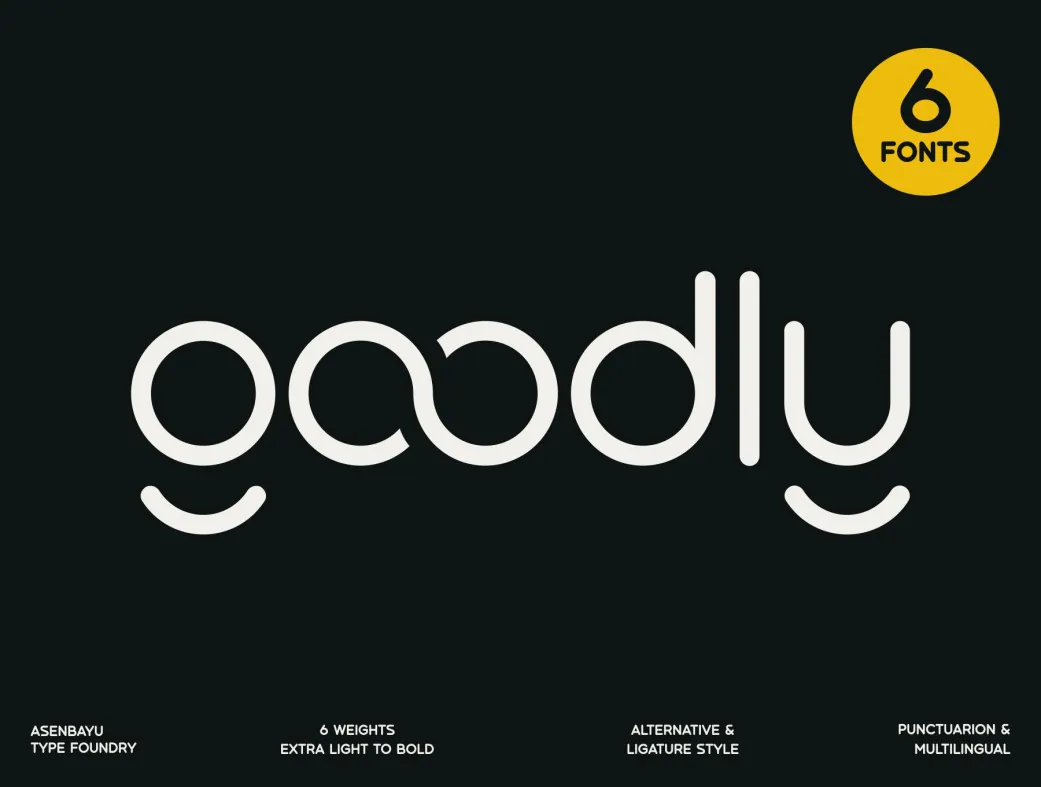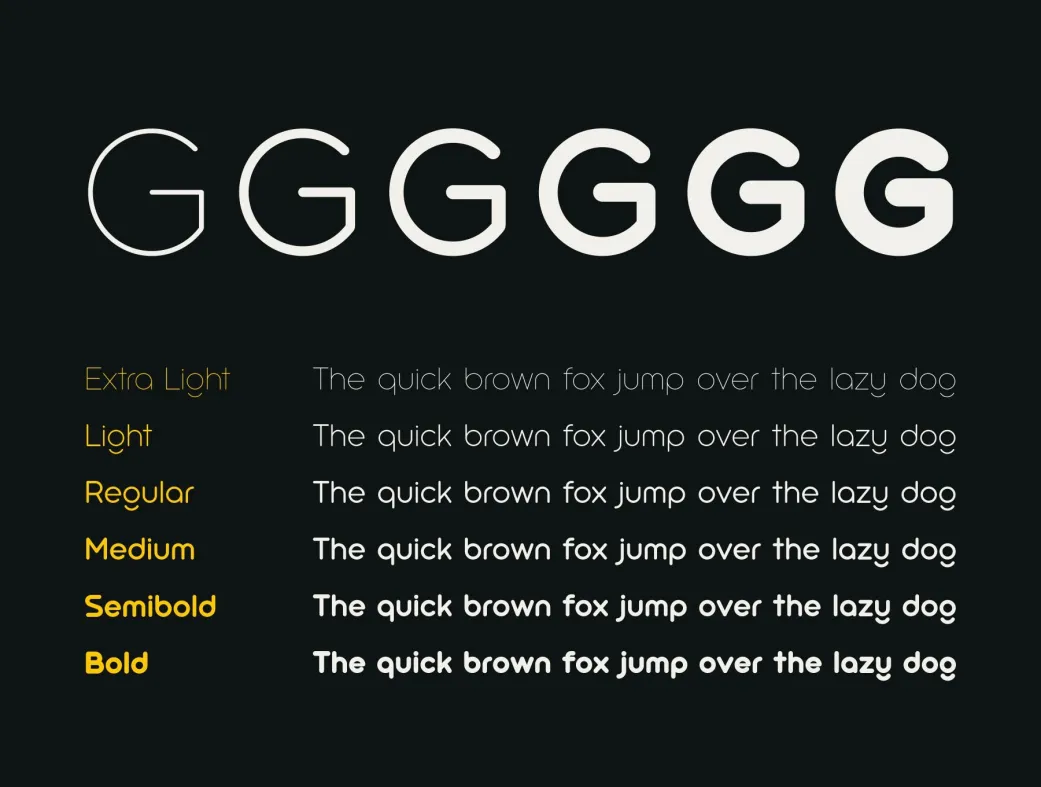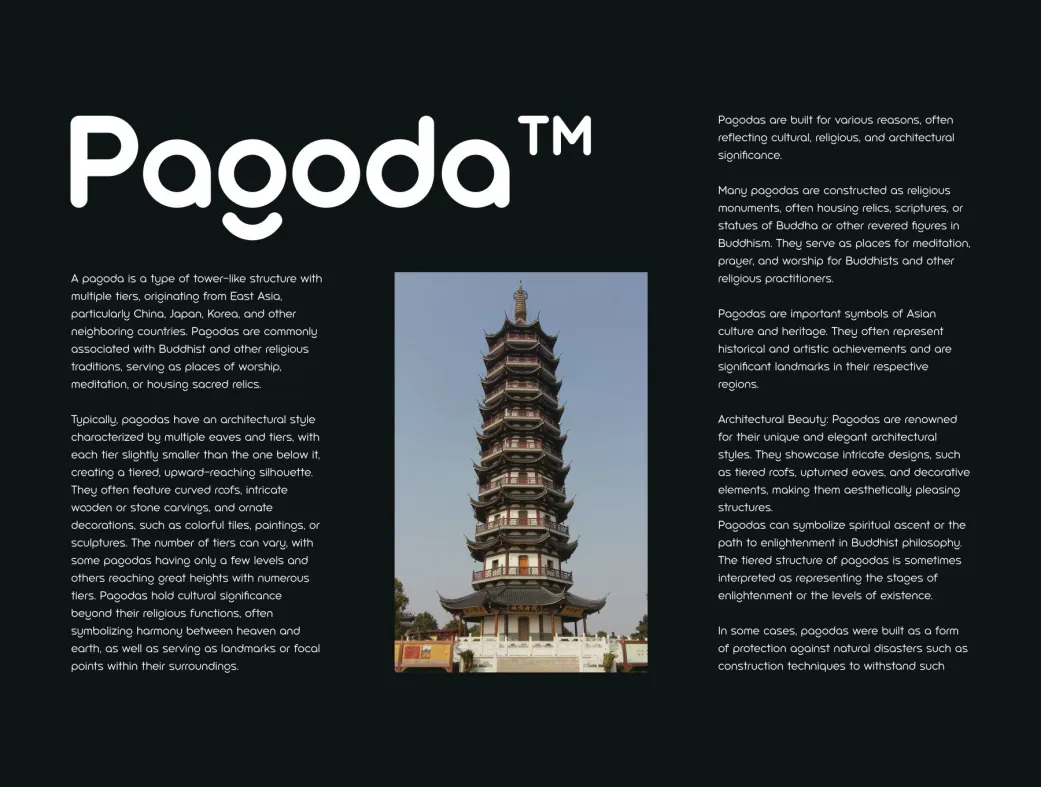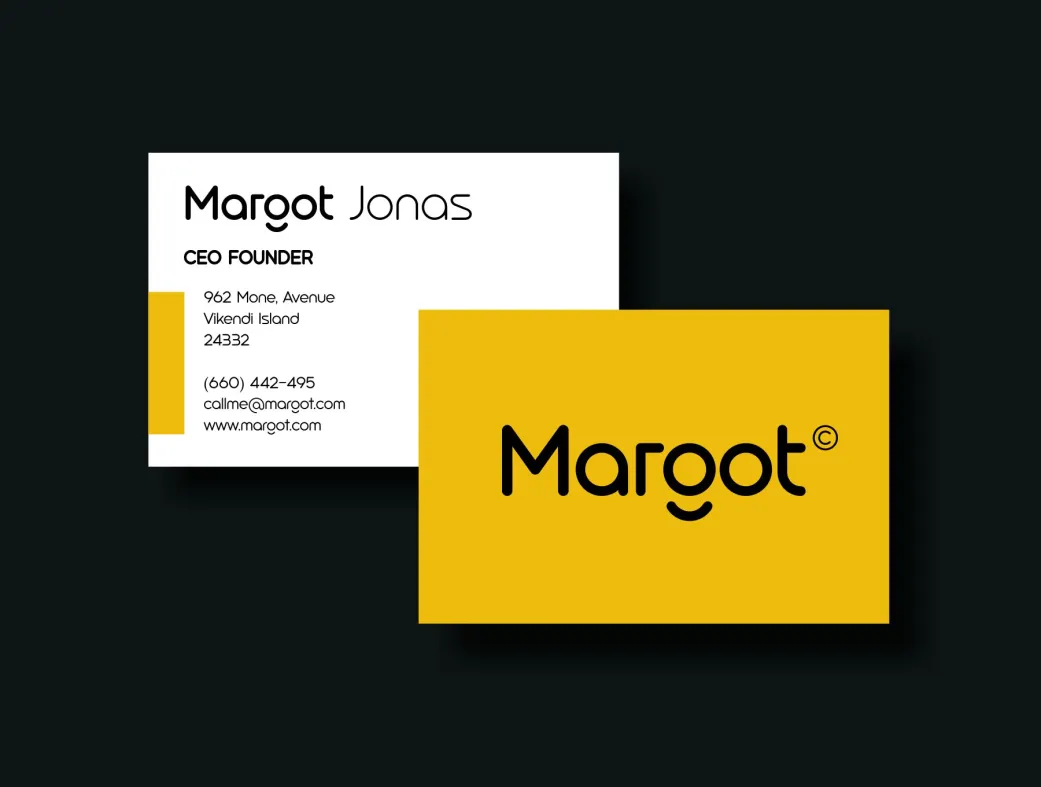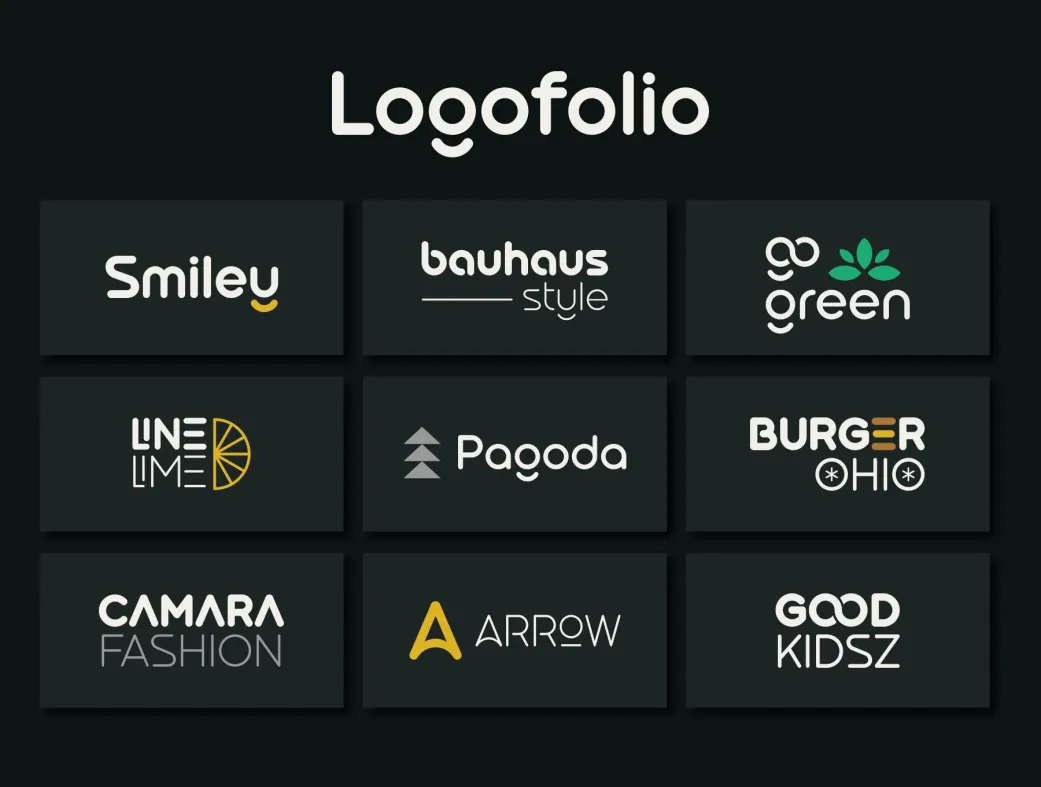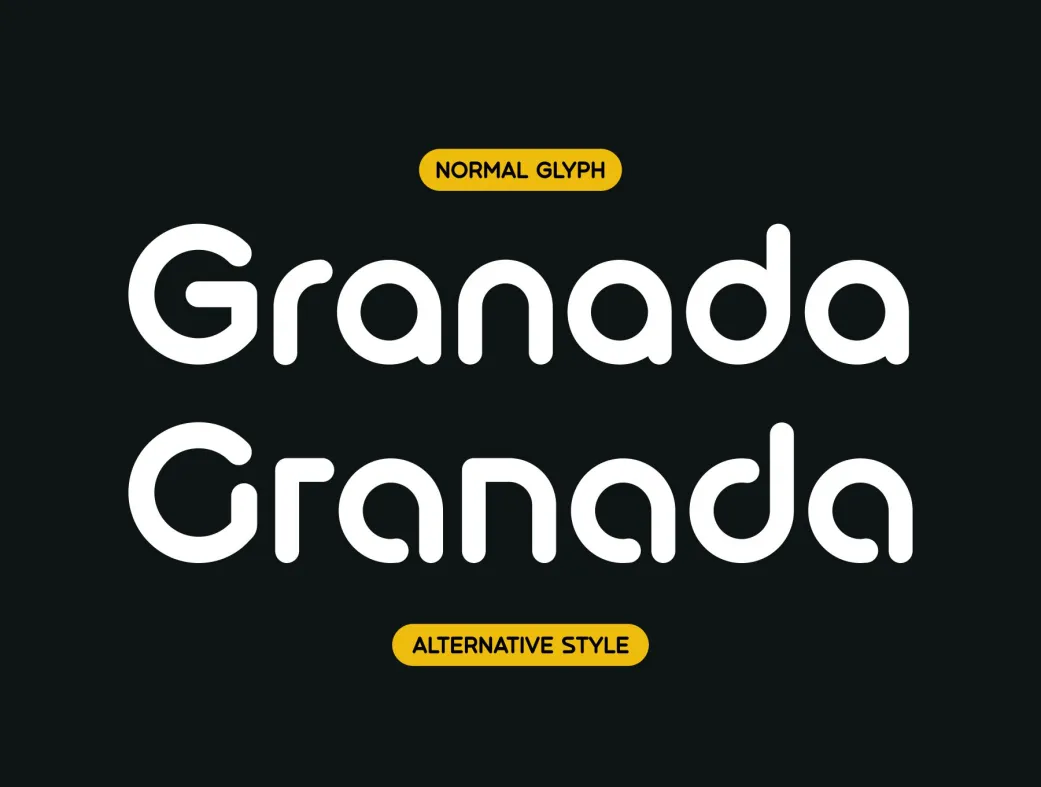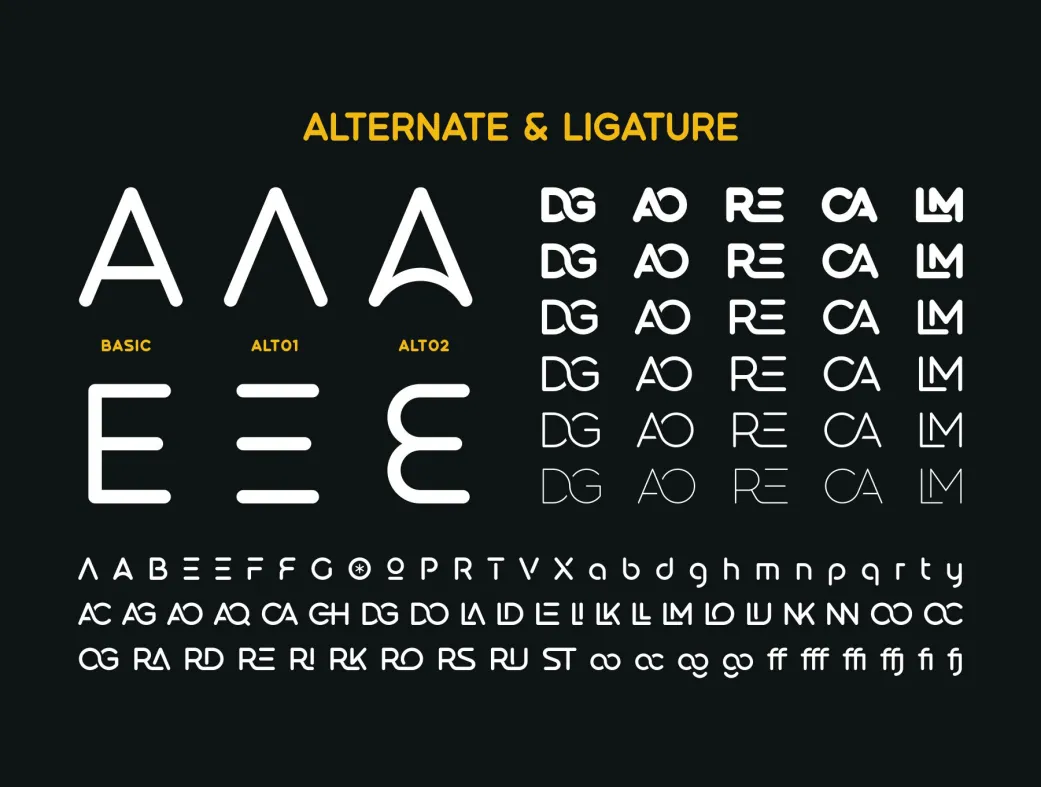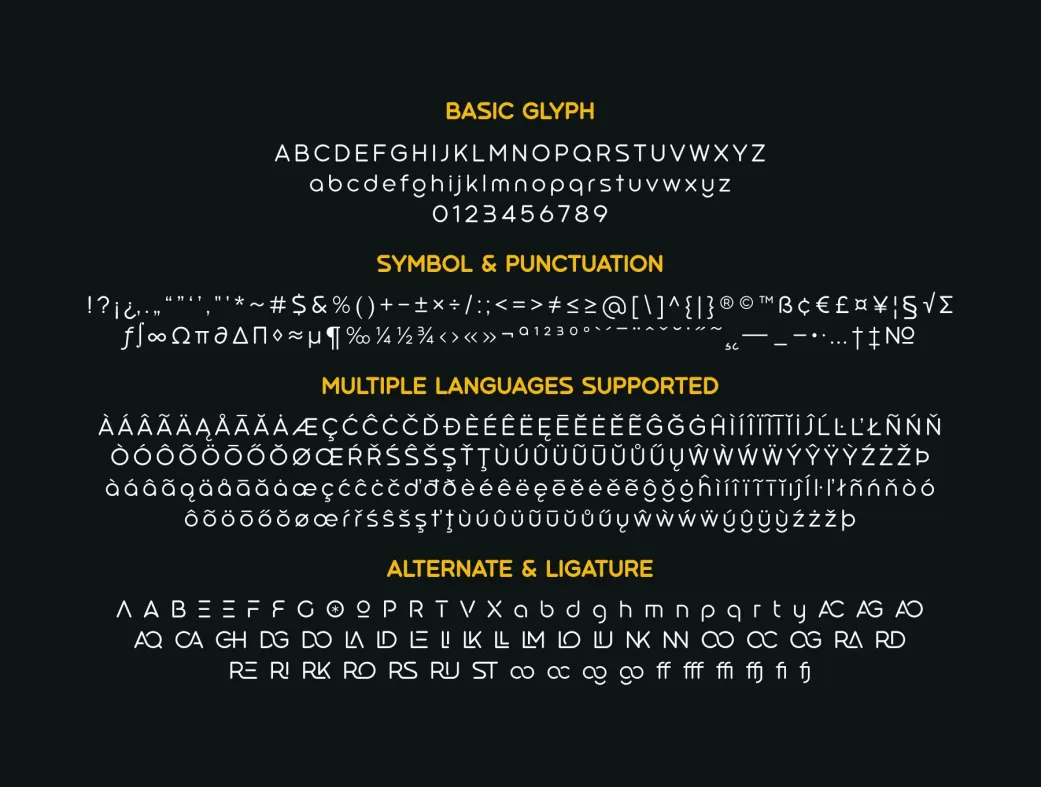
خانواده فونت‌ گودلی | Goodly
خانواده فونت Goodly با ۶ وزن مختلف، طراحی‌های شما را به زیبایی متمایز می‌کند!
Goodly Fonts Family
خانواده فونت‌ گودلی | Goodly Font Family
خانواده فونت‌ Goodly یک مجموعه فونت مدرن و گرد با طراحی سنس سریف است که شامل ۶ وزن مختلف می‌باشد. این فونت به شما کمک می‌کند تا تعادل ایده‌آل طراحی را بین مدرنیته و سادگی برقرار کنید. شکل گرد این فونت‌ها می‌تواند احساس دوستی را ایجاد کند، در حالی که همزمان ظاهری حرفه‌ای نیز دارند.
خانواده فونت Goodly با ۶ وزن مختلف، قابلیت‌های متنوعی را برای طراحان فراهم می‌آورد. این فونت‌ها از فرمت‌های OTF، TTF و WOFF پشتیبانی می‌کنند و دارای گلیف‌های استاندارد هستند. همچنین، Goodly شامل جایگزین‌های استایلی و لیگاتورهای جذابی است که به شما امکان می‌دهد طراحی‌هایی منحصر به فرد و زیبا ایجاد کنید. با وجود پشتیبانی از چندین زبان، این فونت برای پروژه‌های بین‌المللی نیز مناسب است و می‌تواند در طراحی برچسب‌های مد روز، لوگوهای خاص و برندینگ، طراحی پوسترها، مد و بسیاری دیگر مورد استفاده قرار گیرد.
این فونت برای طراحان حرفه‌ای و مبتدی مناسب است. طراحان حرفه‌ای می‌توانند از تنوع وزن‌ها و جایگزین‌های استایلی برای ایجاد پروژه‌های خاص استفاده کنند. در عین حال، مبتدیان نیز می‌توانند به سادگی از این فونت در طراحی‌های خود بهره‌برداری کنند و به راحتی با آن آشنا شوند. توصیه می‌شود که در طراحی‌های برندینگ و تبلیغات، از این فونت برای جذب مخاطب و ایجاد احساس مثبت استفاده شود.
1. آیا فونت Goodly شامل وزن‌های مختلف است؟
بله، خانواده فونت Goodly شامل ۶ وزن مختلف است که به شما امکان می‌دهد تا در طراحی‌های خود تنوع ایجاد کنید.
4. آیا این فونت مناسب طراحی‌های برندینگ است؟
بله، فونت Goodly به دلیل طراحی مدرن و دوستانه‌اش، گزینه‌ای عالی برای طراحی‌های برندینگ و تبلیغات است.